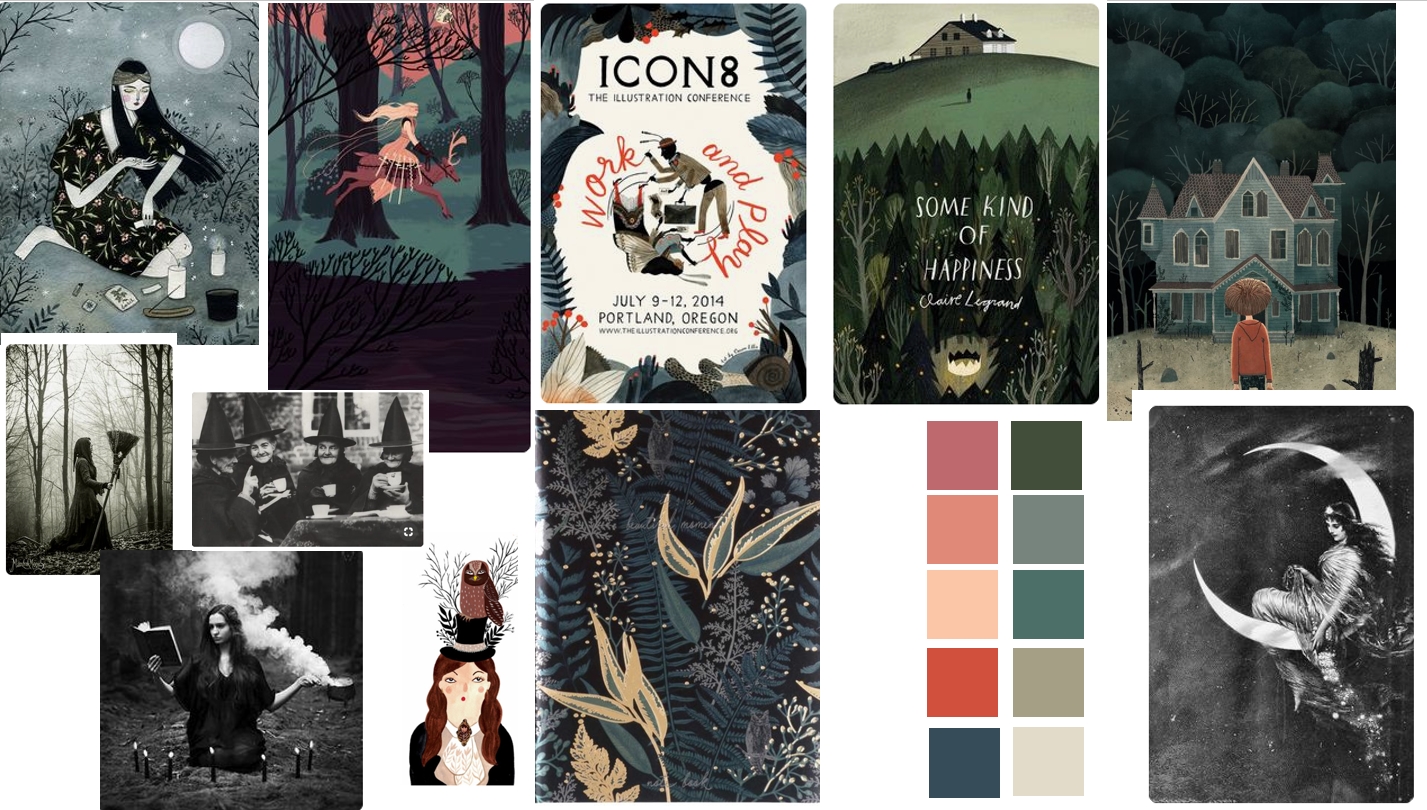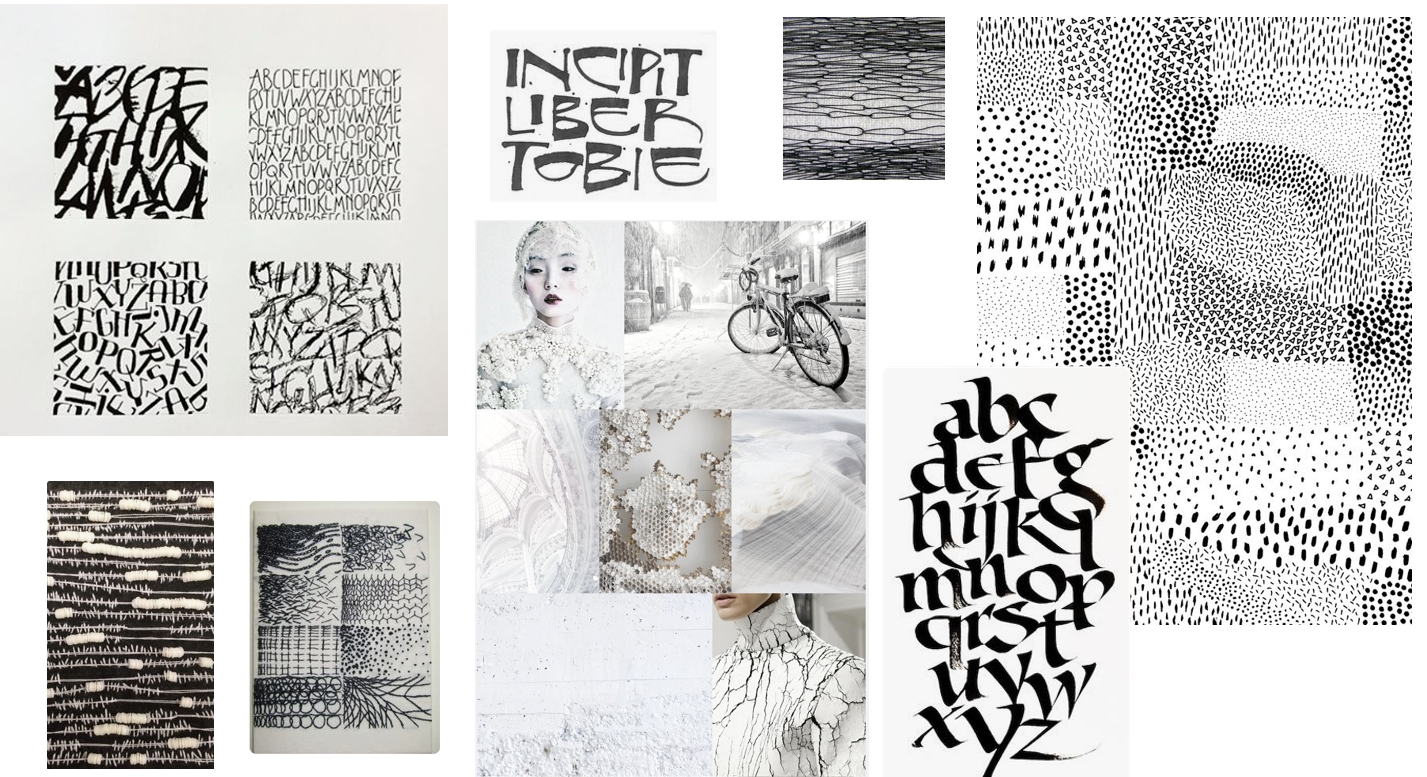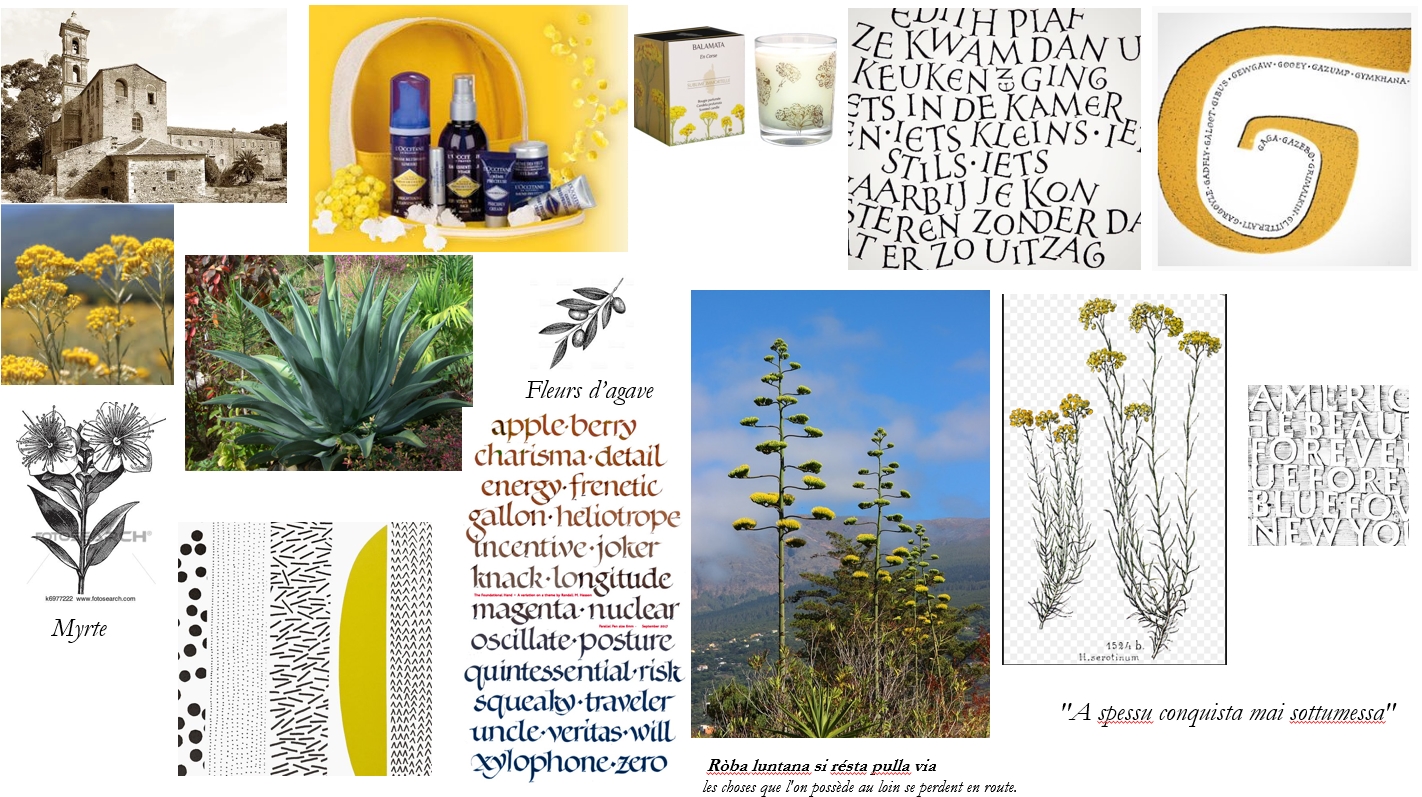
Souvent ce ne sont pas les idées qui manquent ou les sources d’inspiration lorsqu’on veut se lancer dans une réalisation un peu finie. Ce qui pose souvent problème, c’est l’organisation des idées et surtout le tri.
Le Moodboard est un tableau d’inspiration, ciblé et structuré. C’est un outil qui est largement utilisé dans la mode pour mettre au point les collections (on parle aussi de planches de tendance).  Réaliser un moodbard permet de faire le tri dans nos recherches et de ne garder que l’essentiel, sur une page idéalement. C’est un peu le contraire de Pinterest, pour ceux.celles qui utilisent beaucoup ce site : en effet sur Pinterest, il est facile de passer des heures à se perdre et à épingler compulsivement tout et n’importe quoi, « au cas où », ou juste parce que sur l’instant cela nous plait.
Avec le moodboard, on est dans une démarche un peu plus cadrée, parce qu’à la base on a déjà une idée un peu précise : on veut faire un tableau sur tel thème, on veut faire un carnet sur un voyage dans tel pays, on veut créer quelque chose dans des tons chauds/froids, on cherche une ambiance de couleurs, de textures etc.
Stade 1 : les recherches
Les recherches peuvent se faire bien sûr sur Pinterest, en gardant en tête un objectif précis pour ne pas se perdre et y passer des heures. Se fixer 30 minutes maximum, par exemple, permet de rester concentrer sur son objectif.
Pendant que je fais des recherches, en général, je m’ouvre un fichier image vierge ou tout simplement un fichier Powerpoint, et je copie/colle au fur et à mesure mes trouvailles. Il est bien sûr possible de créer un moodboard sur une vraie feuille, sur laquelle vous collez au fur et à mesure vos inspirations. C’est moins rapide, mais cela fonctionne bien aussi et vous pouvez l’enrichir avec des idées écrites à la main, etc.
Pour les recherches, j’ai quelques pistes d’investigation qui sont toujours les mêmes :
• Les couleurs
• Les typos / styles calligraphiques
• Des histoires : une ambiance de vacances, des personnages, un thème etc…
• Des textures
Astuces :
• Pinterest est bien plus pratique qu’une simple recherche Google image car tout est déjà logiquement indexé,
• Ne négligez pas quelques recherches en dehors du web… Dans vos livres, vos magazines, des bouts de tissus : vous pouvez prendre des photos, et les intégrer dans votre moodboard.
Stade 2 : le tri
Si vous avez sélectionné 40 images, il y en a à peu près… 20 de trop. Visuellement, il faut que ce que vous souhaitez capter dans votre moodboard soit évident, donc il faut resserrer la sélection :
• Faites le tri
• Demandez-vous si votre tableau est cohérent.
• Demandez-vous si votre tableau est bien dans la cible que vous vous êtes fixé.e au départ ou si vous n’êtes pas en train de dévier. Cela peut donner naissance à un second moodboard !
Stade 3 : imprimer le moodboard
Ça c’est personnel, mais j’aime bien imprimer un moodboard une fois qu’il est terminé, pour l’avoir tout le temps sous les yeux quand je travaille. C’est un peu une boussole, en fait. Cela permet de ne pas trop dériver et de coller à son idée première (même si bien sûr les idées peuvent évoluer en cours de route).
Quelques exemples de moodboard réalisés récemment
Un moodboard graphique, noir et blanc
Ce moodboard a été fait pour une future réalisation en calligraphie. On est dans du graphique, du noir et blanc, du rythme et du contraste. Vous voyez qu’il y a de l’écriture, mais pas seulement… il y a des images qui viennent de broderies, des photos, des matières.
Le moodboard pour mon carnet de voyage
J’avais fait un petit moodbard pour mon carnet de voyage cet été, histoire de rassembler des pistes, des inspirations. J’étais dans l’été, la Corse, les tons citron et bleu, le carnet de voyage.
Le moodboard féérie et sorcellerie
Celui est très récent, c’est pour le challenge #folktaleweek sur Instagram qui se tient en ce moment. On est dans le conte, l’hiver, le mystère, la nuit, la magie, et un peu de sorcellerie… Ce tableau m’a aidée à sélectionner ma palette de couleur et la tonalité de ce que je voulais faire.
Le moodboard Lettres & Co
Et oui, j’avais fait un moodboard pour la charte graphique du blog : couleurs principales, bannière, etc. Je voulais quelque chose avec des tons vifs, chauds, tranchés, du graphique avec des inspirations de la nature.
Dans ce moodboard, il y a la moitié des photos qui sont des réalisations personnelles, comme les encrages de végétaux ou le carreau « l’art c’est la santé ». L’idée était de partir de ce que je fais, de ce que j’aime et d’en sortir une charte graphique.
Les moodboards tout faits
Ça existe, et c’est très sympa, très inspirant. Vous en trouverez beaucoup sur mon tableau Inspiration|Couleur sur Pinterest. Mais ce n’est pas VOUS : donc si vous créez un moodboard pour une réalisation future, faites plutôt vos propres recherches et vos propres sélections !
J’ai toujours travaillé un peu comme ça, et d’autant plus pendant le MATSBOOTCAMP où on avait 15 jours pour traiter un sujet précis. Sinon je suis un vrai électron libre avec 10 mille trucs en tête qui se caracolent joyeusement et au final rien n’en sort parce que c’est trop la pagaille 😉